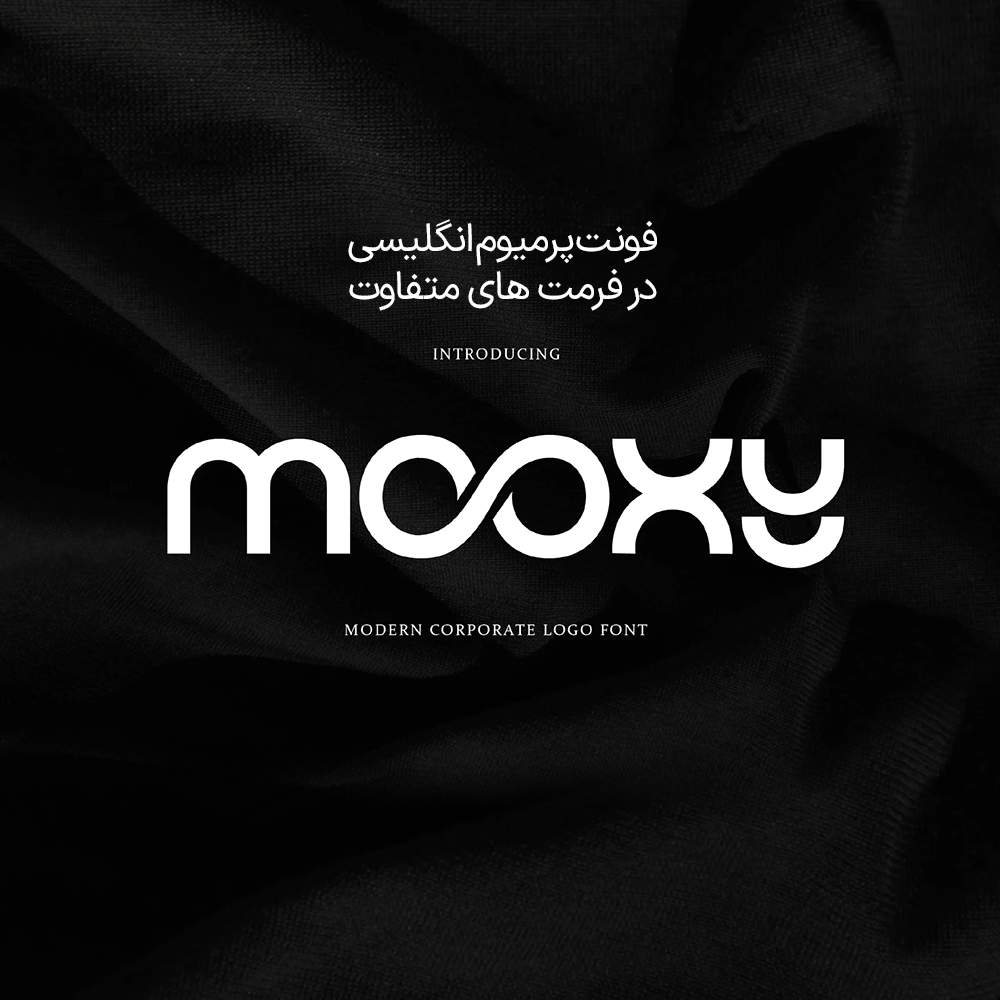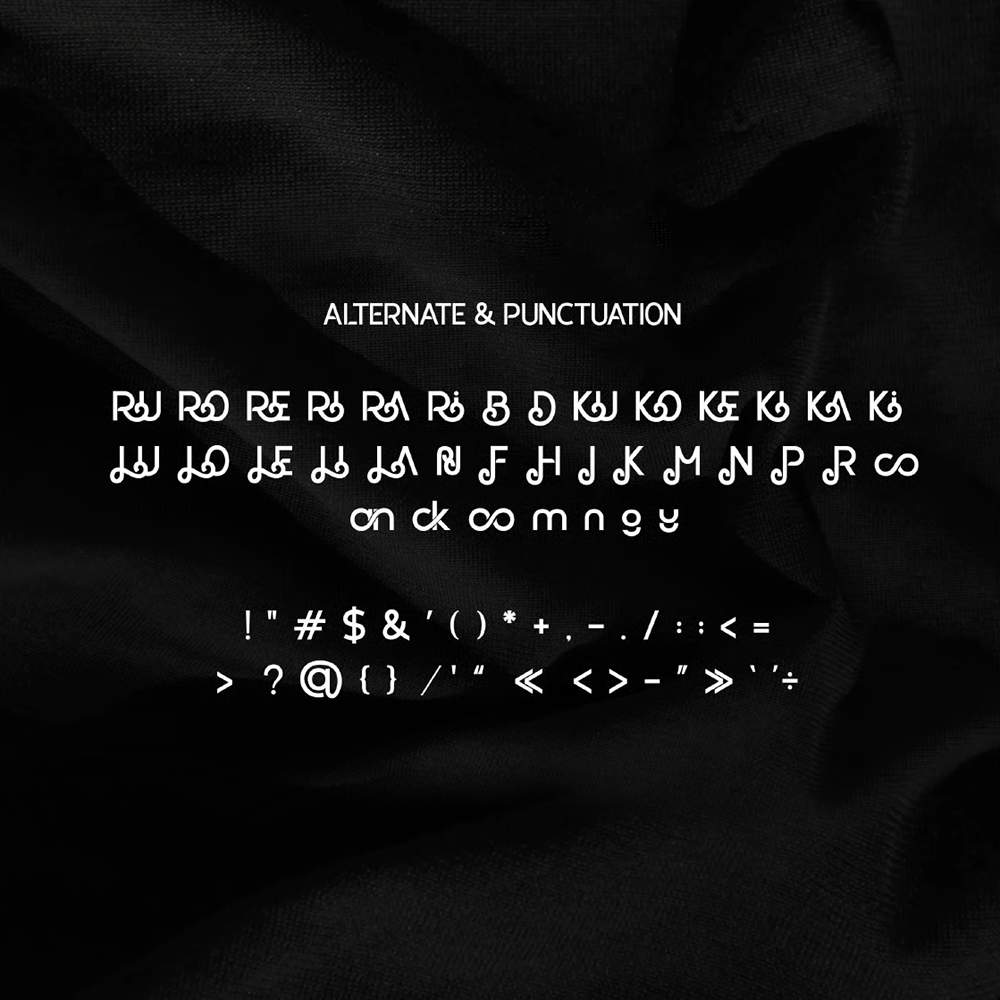
دانلود فونت انگلیسی Mooxy Font
فونت پرمیوم و انگلیسی Mooxy Font یک فونت لوگوی مدرن است که برای ایجاد ظاهری شیک و حرفهای در پروژههای برندسازی و هویتسازی طراحی شده است. این فونت با خطوط تمیز و سبک معاصر خود، برای لوگوها، برندسازی تجاری، بستهبندی، هدر وبسایت و مطالب بازاریابی عالی است. Mooxy ظاهری پیچیده و در عین حال مینیمالیستی ارائه میدهد و آن را برای مشاغل و افراد خلاقی که به دنبال یک هویت بصری جسورانه و به یاد ماندنی هستند، ایدهآل میکند.
مزایای استفاده از فونت لاتین Mooxy Font چیست؟